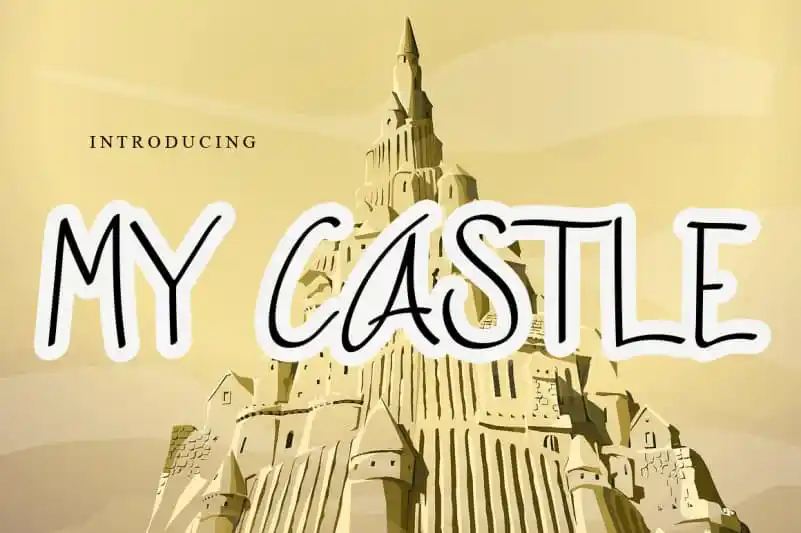
A My Castle Font é uma elegante fonte manuscrita que transmite uma sensação leve e fresca. Seu estilo natural e único se torna perfeitamente adequado para um amplo range de designs, limitados apenas pela imaginação do criador. Esta fonte é ideal tanto para criações gráficas elaboradas quanto para trabalhos menos complexos, proporcionando uma adicional de elegância sem exagero ou formalidade excessiva. Com a My Castle Font, as possibilidades são realmente imensas e seu potencial se estende a cada projeto. Seja um mural criativo, um cartão personalizado ou até mesmo um poster de arte, esta fonte manuscrita tem tudo o que você precisa para dar vida ao seu design com uma sensação única e autêntica. Em termos de categoria de design, ela pertence à Handwritten Fonts.